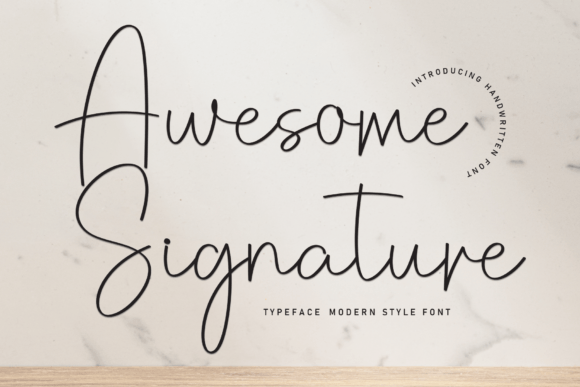
Awesome Signature
Awesome Signatureのような高品質の素材をお探しの場合、このプレミアムパッケージはクリエイティブなプロジェクトに素晴らしい選択です。
POD(オンデマンド印刷)製品、結婚式の招待状、またはソーシャルメディアのグラフィックを作成している場合でも、Awesome Signatureは理想的です。